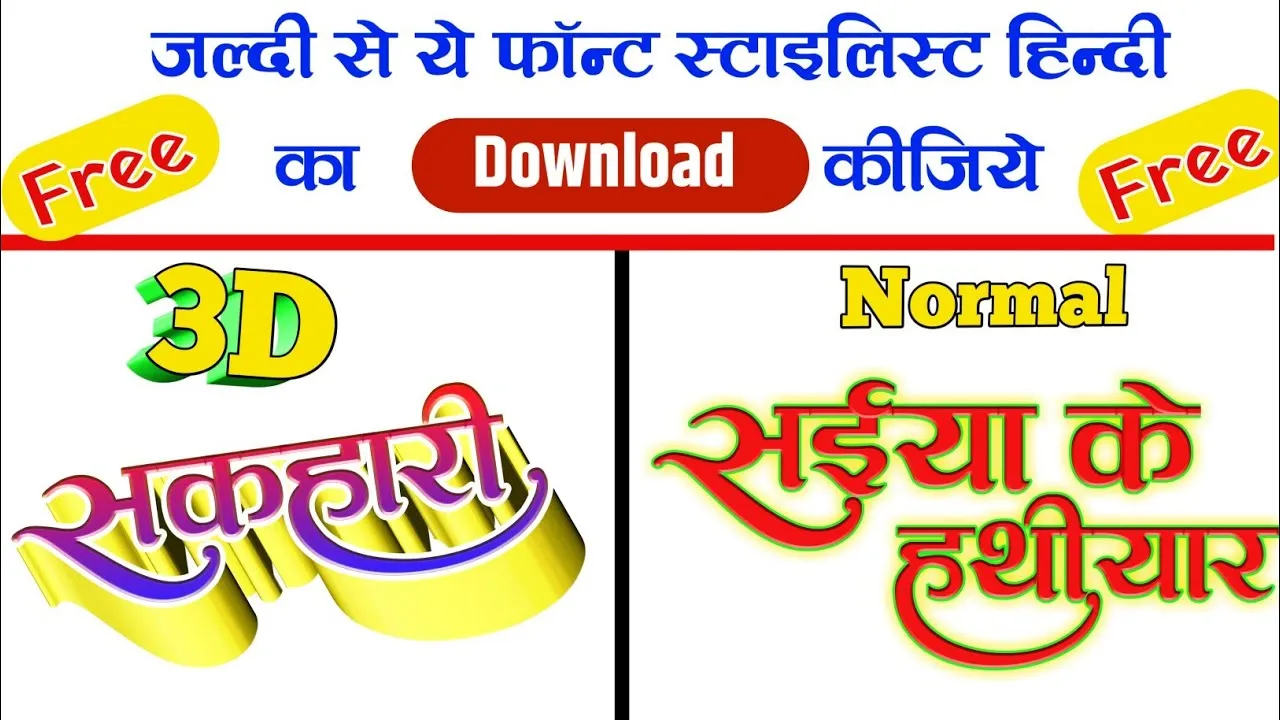
рдирдорд╕реНрдХрд╛рд░ рджреЛрд╕реНрддреЛрдВ рдЖрдк рд╕рднреА рдХреЛ рдмрд╣реБрдд-рдмрд╣реБрдд рд╕реНрд╡рд╛рдЧрдд рд╣реИ Technical pts.in рд╡реЗрдмрд╕рд╛рдЗрдЯ рдкрд░ рддреЛ рдЖрдЬ рд╣рдо рдЖрдк  рдХреЛ рдПрдХ рдРрд╕рд╛ font рджреЗрдиреЗ рд╡рд╛рд▓реЗ рд╣реИ рдЬреЛ  рд╣рд┐рдВрджреА рдХрд╛ рдлреБрд▓ рд╕реНрдЯрд╛рдЗрд▓рд┐рд╢ font рд╣реИ рдЗрд╕ font рдХреЛ рдЖрдк рдпрд╣рд╛рдВ рд╕реЗ рдЖрд╕рд╛рдиреА рд╕реЗ рдбрд╛рдЙрдирд▓реЛрдб рдХрд░ рд╕рдХрддреЗ рд╣реИрдВ-